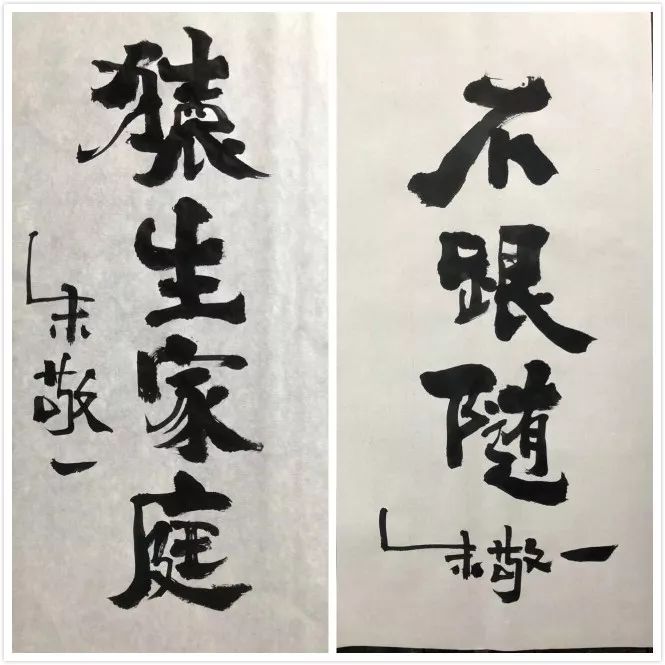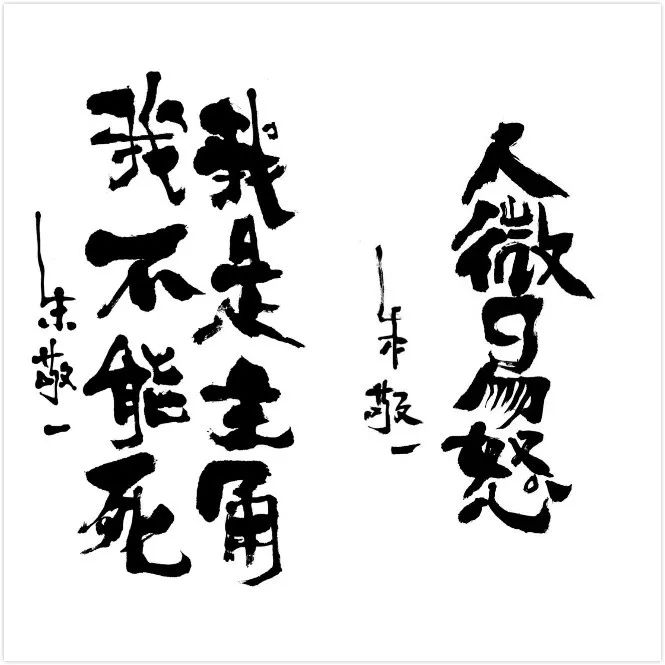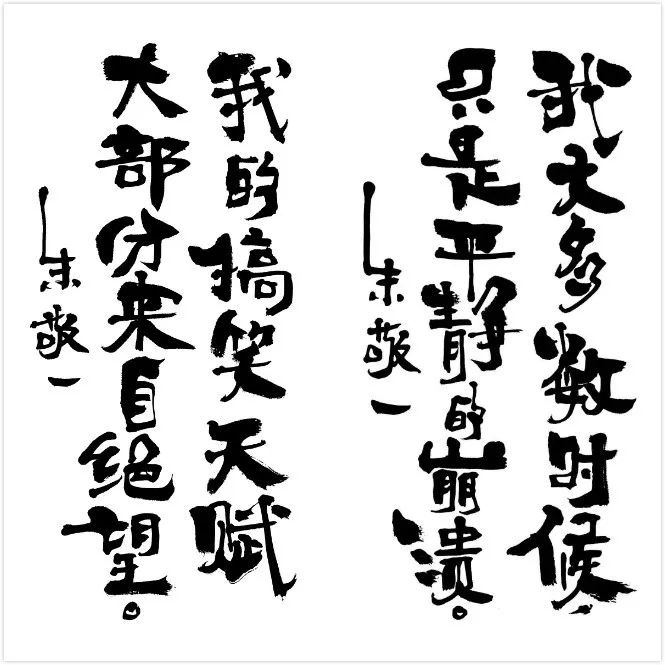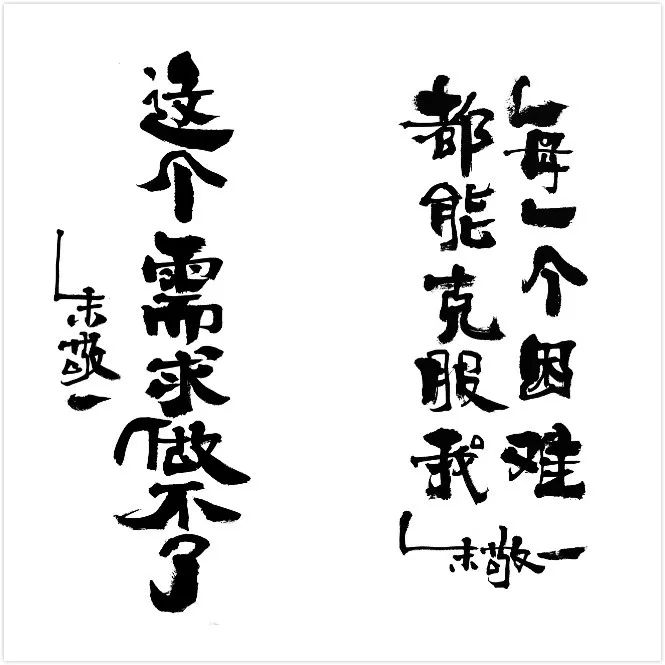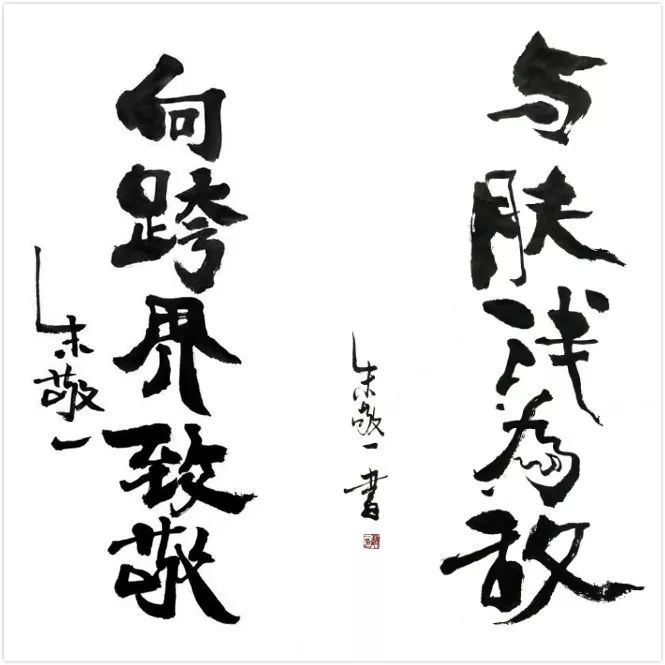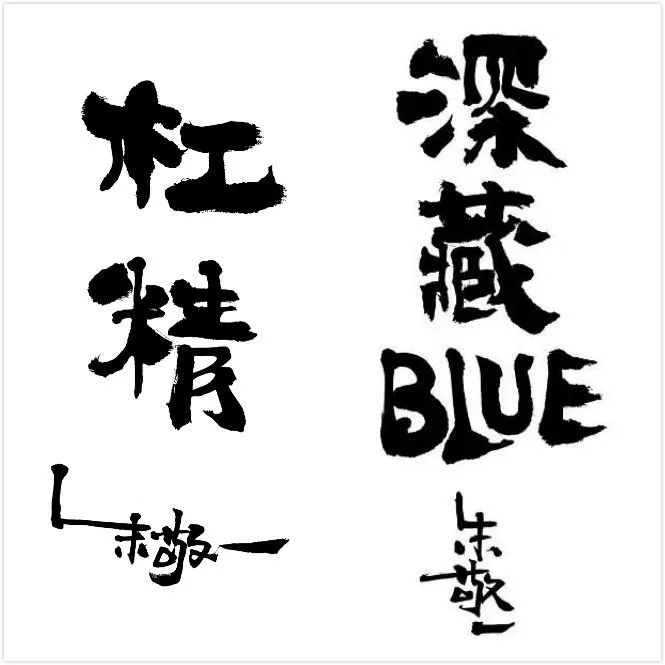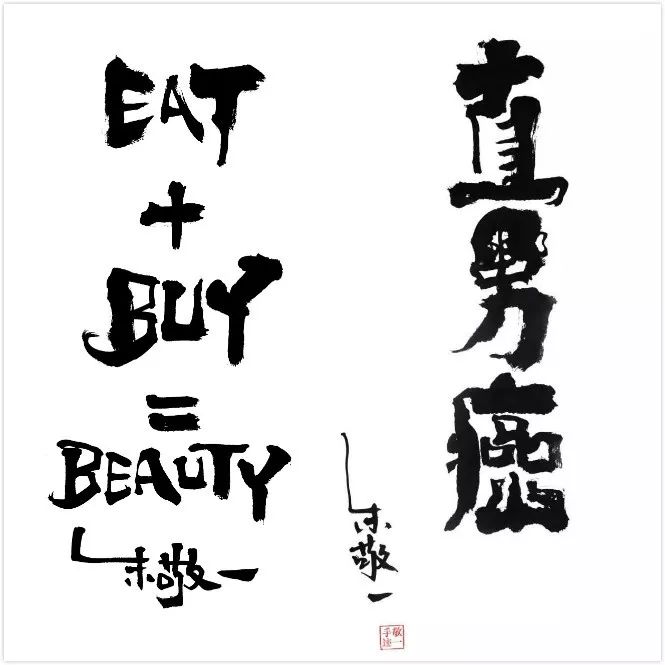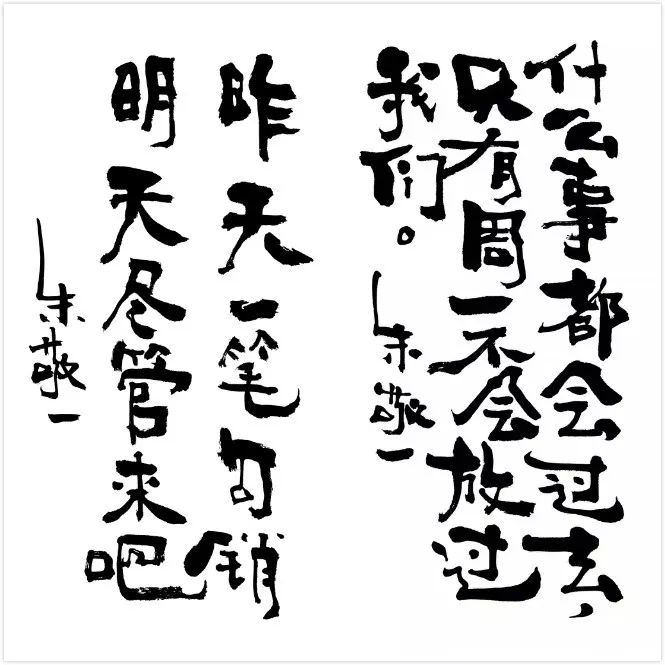
只有设计师才会懂的49句脱胎换骨的毒鸡汤
要问平时柚子最喜欢什么,除了剥柚子吃,就是喝点毒鸡汤了,绝对提神醒脑,比咖啡还好用。
可单单看还觉得冲击力不够,如果把它跟书法结合在一起,那以毒攻毒的魔力,真真是碉堡了!
南门书法的创始人,朱敬一就做到了,他的笔风不走寻常路,不楷不隶不篆不草,有着鲜明的个人特征(无法山寨)。
看过的人,都想把他挂在家里,印在衣服上。不过柚子觉得你只要收藏这篇文,每天看看,效果也是一样的,设计师走起吧!
你的痛点我懂
现在好像不秃,都不好意思跟人聊天,说明工作没用心啊!所以除了默默囤生发剂,就是安慰自己,没什么可怕的,威廉王子跟我一样。
不过面子工程还是可以通过人民币解决的,所以没事早点睡,有空多挣钱!
别人眼中的你
跟甲方爸爸对话的时候,永远是杠精,而在同事面前,永远保留着绝招,等待适当的机会,一呼成名,“你好厉害啊”!
不过生活中,女设计师只会吃吃吃,买买买,而男程序猿只会一根肠子通道底~
他们的人生信条,大概就是想做野猪系男子,不跟随!
你最喜欢说这些
下面这些就算你没全说过,肯定也说其中一句,就算你嘴上没说过,心里也说过一百次了,特别是那句“做牛做马,别做乙方”,哈哈!
怎么看怎么有道理
有时候想不通的时候,就吃点下面的解药,你会觉得人生豁然开朗,毕竟吐槽是一门学问,能吐到心里就更nice(耐撕)了。
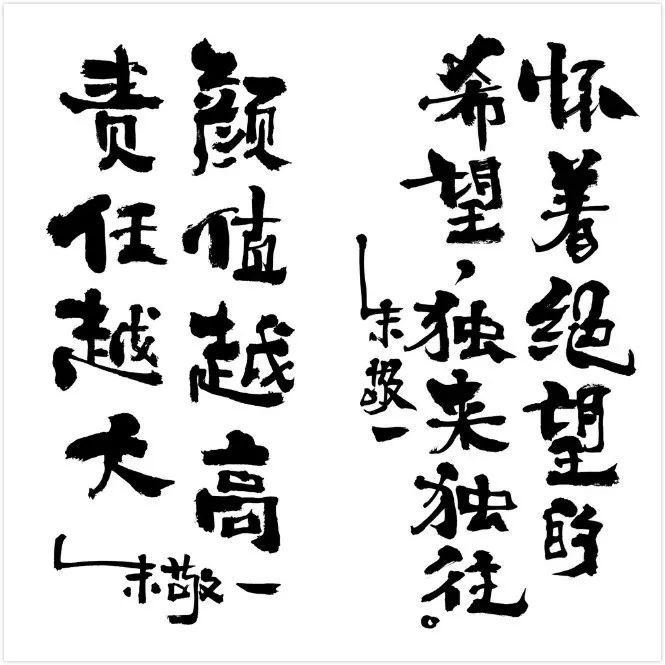
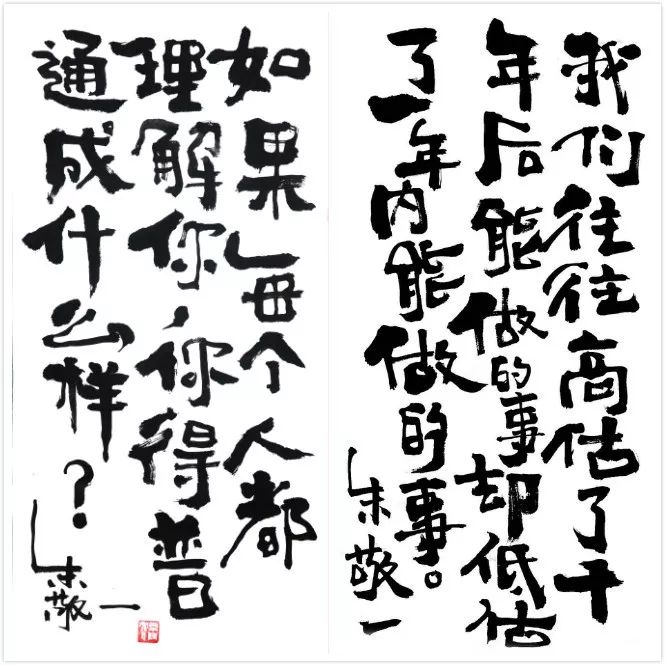
你要修炼成这样
很多人总想改变同事、改变boss、改变甲方,但却一次次碰钉子,知道原因是什么吗?就是心太大,总觉得宇宙(怎么那么像字由,哈哈)在我手中,其实你就是人类(人累)而已,所以别太较真,毕竟人间不值得!